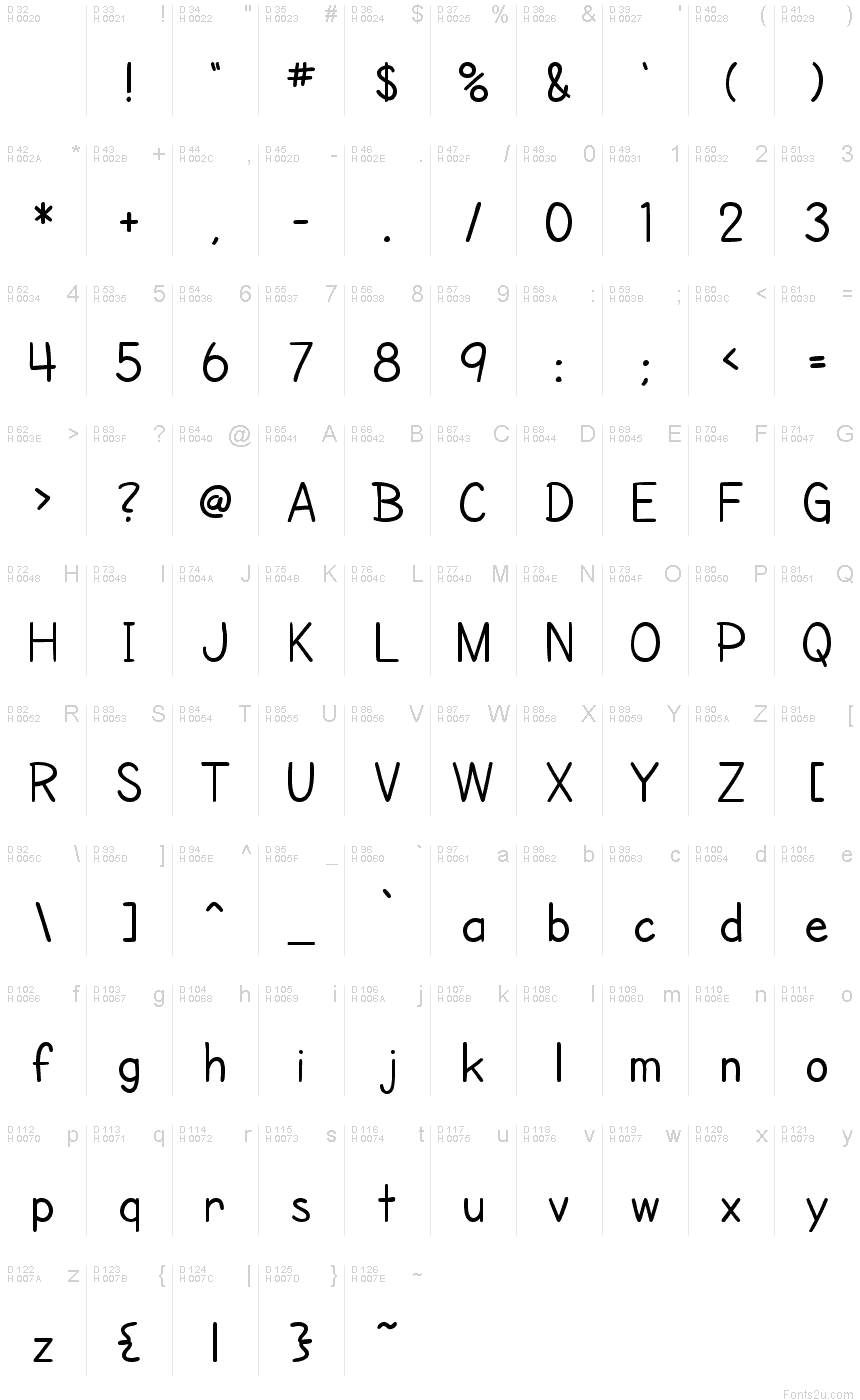
SF Cartoonist Hand von ShyFoundry ist eine kostenlose, handschriftliche Schrift im Cartoon-Stil, die mit der leichten Dynamik von Marker-Schriftzügen für Comic-Captions und lockere Titel überzeugt. Die Buchstaben wirken offen und abgerundet, mit sanften Strichen, hohen, vereinfachten Formen und einem verspielten Rhythmus, der das Schriftbild leicht und ordentlich hält.
Sie passt perfekt in Comic-Strips, Kinderbuchcover, Scrapbook-Überschriften, Poster und freundliche Verpackungen, wo ein kostenloser Font mit dieser handgezeichneten Wärme kurze Zeilen ohne Steifheit aufwerten kann. Verwenden Sie ihn für Titelschilder, Sprechblasen-Texte, Kapitelanfänge oder einfache Logos, wenn Sie diesen sauberen Cartoon-Touch anstelle einer groben Pinsel-Optik suchen.